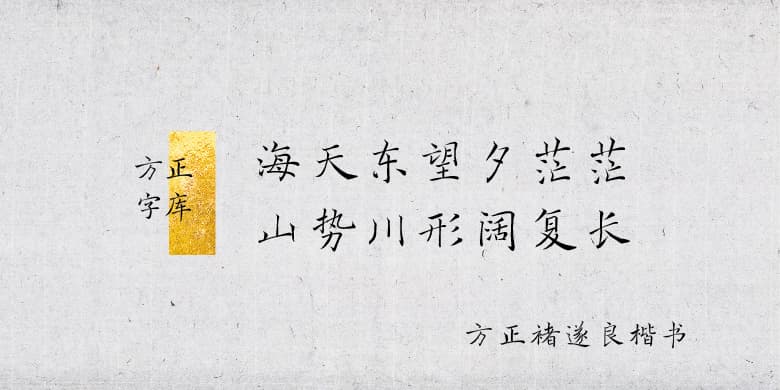
品牌:方正字库中华精品字库设计师:王大禾发行时间:2021字库编码:大陆简体(GB2312-80)分类:常规书写·毛笔字体属性:精品字
关于褚遂良:
褚遂良(596~658/659年),字登善,出身河南褚氏,博学多才,精通文史。唐朝政治家、书法家。与欧阳询、虞世南、薛稷并称“初唐四大家”,传世代表作品有《孟法师碑》、《雁塔圣教序》等。
字体特征:
以《雁塔圣教序》为临创开发依据;字体略显隶意,又流畅如行书,笔画处理上粗细变化丰富,线条瘦劲而秀润,耐人寻味;结字上中宫紧收,四维放开,紧密中有舒展,落落大方。
应用场景:
临创者:王大禾
整理/设计:崔艳、尹涛、陆原、刘婷婷、王洁、史通通、年睿莹、张璋、朱娜
审稿专家:刘洪彪、李有来、朱培尔、虞晓勇、邵佩英、张志庆、仇寅